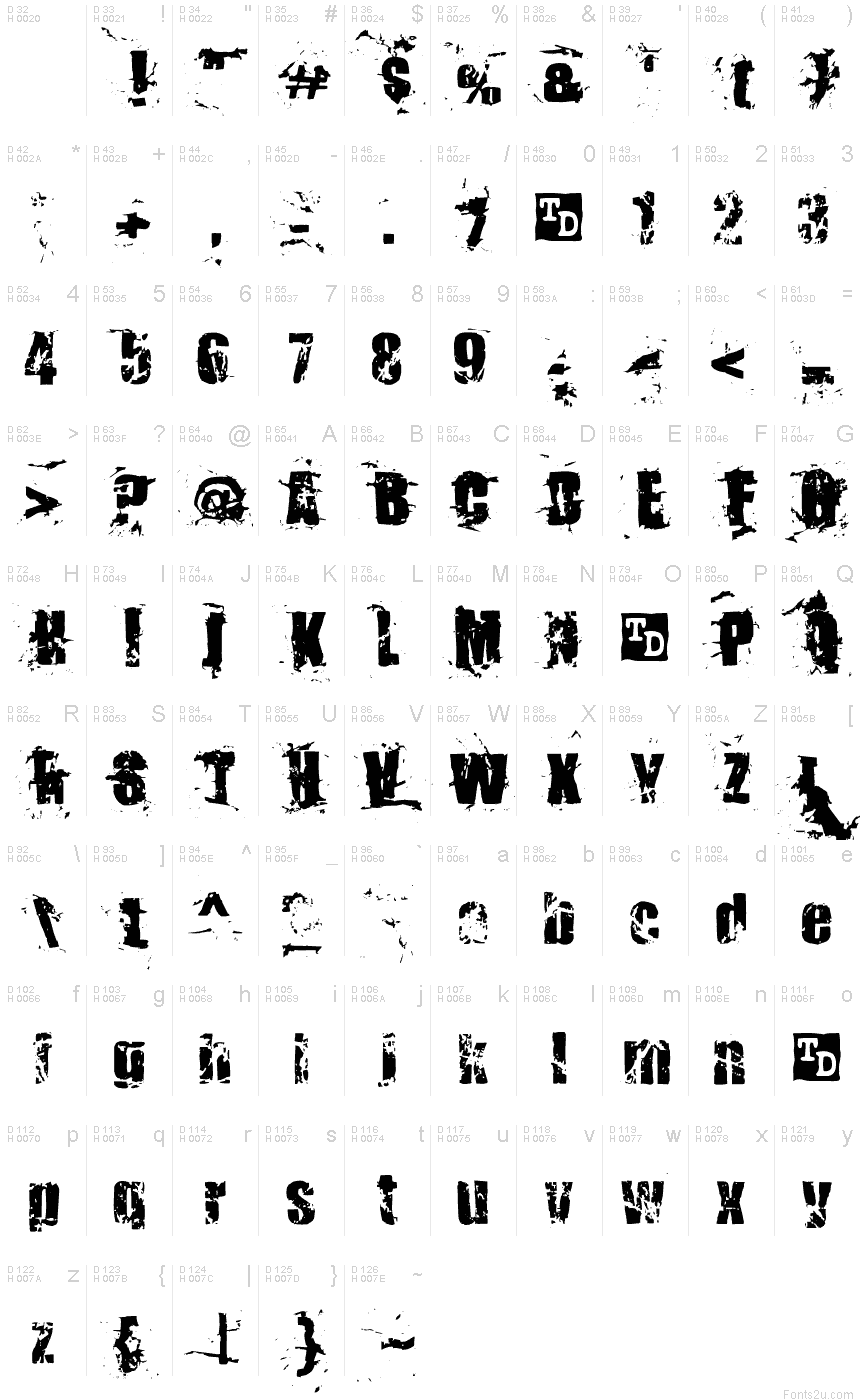
Killer Ants autorstwa Todda Devera to darmowy, postarzany krój typu display, który wygląda, jakby został przeżuty i rozpryskany na stronie. Grube, blokowe litery są nadgryzione, poszarpane i pełne surowych, białych ubytków, co nadaje nagłówkom zniszczony, postapokaliptyczny charakter. Jest surowy i wyrazisty, jak tusz naniesiony na gazetowy papier i pozostawiony na pastwę czasu.
Dzięki Killer Ants nadasz plakatom horrorów, punkowym ulotkom, zaproszeniom na imprezy zombie, tytułom gier, okładkom albumów czy oznaczeniom w domach strachów naprawdę drapieżnego klimatu. Ten darmowy font najlepiej sprawdza się w dużych rozmiarach; w mniejszym tekście zastosuj czysty, bezszeryfowy krój, aby nie konkurował z jego chaotyczną fakturą.